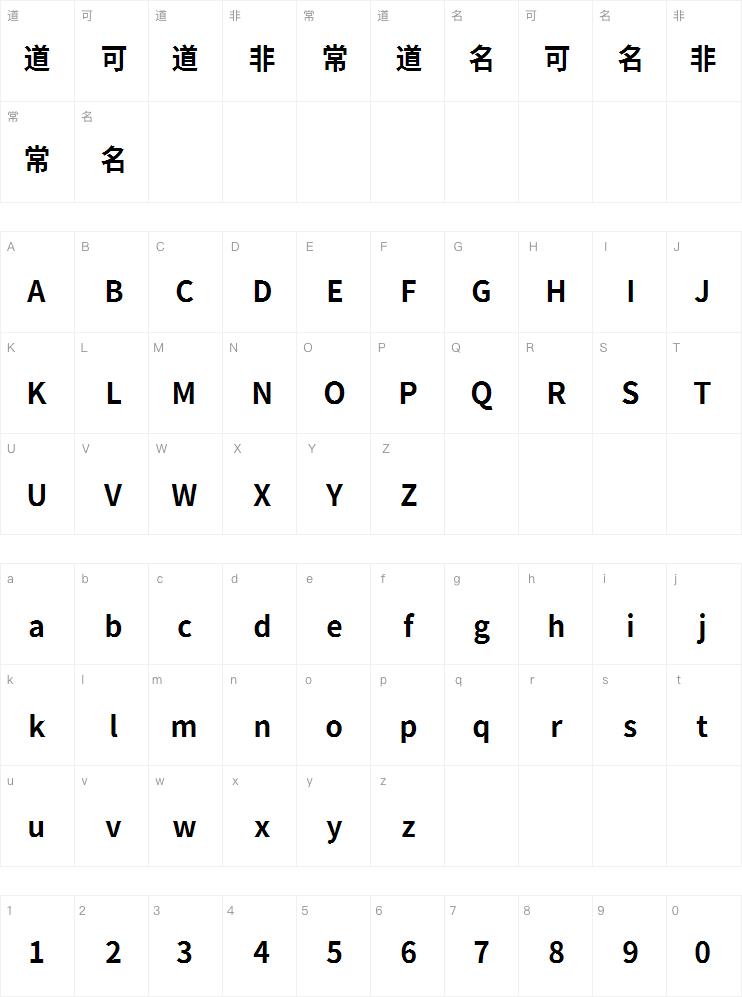
kniu黑体-bold
Kniu Hei 是一套 7 字重的现代简体中文字体家族,含 22,365 个字形,提供 TTF / WOFF / WOFF2 / EOT 四种格式。它将 CJK 字形横向收窄 5%、纵向拉升 3%,形成瘦长挺拔的紧凑字面(「永」字宽高比 0.937),并统一了 Windows 与 macOS 的默认行高。字重覆盖 LightExtra 200 至 Heavy 900,支持简繁中文、日文假名、拉丁、希腊与西里尔。采用 SIL Open Font License 1.1 授权,该字体由设计师buller创作提供,可免费商用。